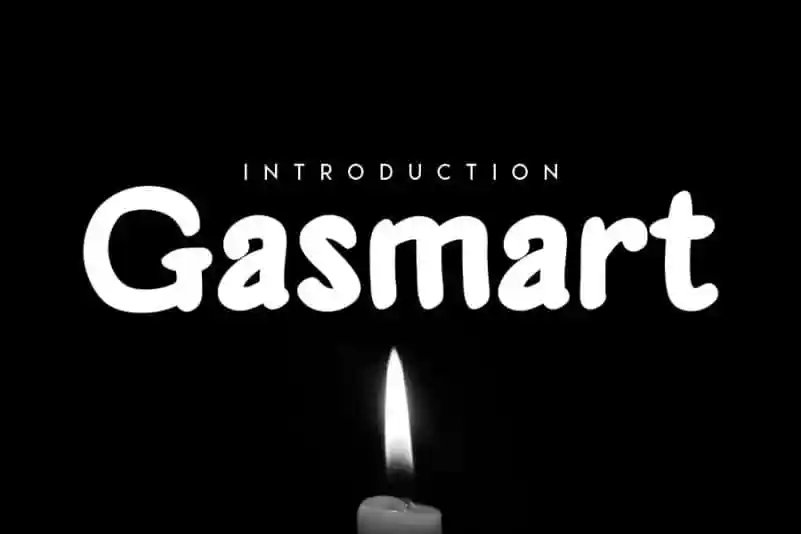
Gasmart Serif Font é uma tipografia serif que traz a elegância do estilo clássico ao seu design com um tom acessível e descontraído. Com sua personalidade amigável, este tipo de fonte se destaca tanto para projetos online como Instagram quanto para criações em calligrafia artesanal para DIY. Seja você designer ou hobbyista, Gasmart Serif será a escolha perfeita para transformar seus ideais criativos em obras de arte inovadoras e autênticas. Ideal tanto para profissionais quanto para entusiastas da design gráfico, esta fonte exala criatividade e facilidade de uso.